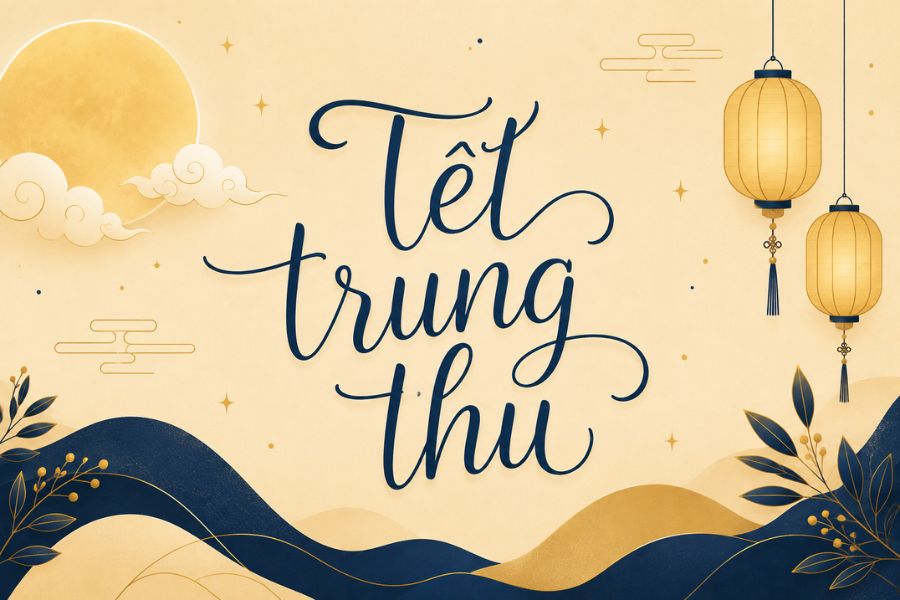
Font chữ trung thu là gì?
Font chữ trung thu là các bộ phông mang phong cách nghệ thuật đặc trưng, mô phỏng nét bút lông thư pháp uyển chuyển hoặc các đường nét tròn trịa gợi nhắc đến hình ảnh vầng trăng rằm. Điểm nổi bật của dòng font này là sự kết hợp giữa tính truyền thống dân gian và nét hiện đại, giúp truyền tải thông điệp về sự đoàn viên, hạnh phúc và thịnh vượng. Trong ngành in ấn, việc sử dụng phông chữ này giúp các mẫu thiết kế trở nên sinh động và đậm chất văn hóa Á Đông.
Tuy nhiên, do đặc thù tiếng Việt có hệ thống dấu thanh phức tạp, nhiều bộ phông quốc tế khi áp dụng vào thiết kế thường bị lỗi nhảy chữ hoặc mất dấu. Bộ font chữ việt hóa trung thu được In Viva chia sẻ đã được tinh chỉnh kỹ lưỡng, đảm bảo từng dấu mũ, dấu thanh đều hài hòa với nét chữ gốc. Điều này giúp các designer tiết kiệm thời gian chỉnh sửa thủ công và tập trung tối đa vào việc sáng tạo bố cục cho các ấn phẩm và bao bì giấy.
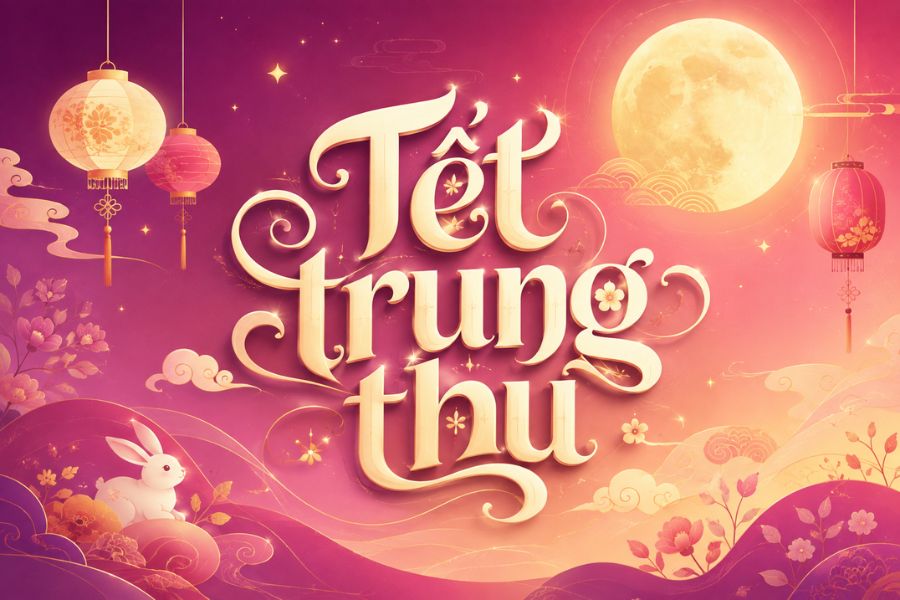
Lưu ý: Khi sử dụng font chữ trung thu đẹp cho mục đích in hộp giấy cao cấp, bạn nên ưu tiên hệ màu CMYK và phối hợp cùng các tông màu đỏ chu sa, vàng kim nhũ để tôn lên vẻ đẹp truyền thống của bộ chữ.
5 ứng dụng chính của font chữ trung thu trong thiết kế và in ấn
Việc sử dụng đúng font chữ giúp nâng tầm giá trị cho món quà tri ân trong mùa lễ hội đoàn viên:
- Thiết kế bao bì hộp bánh trung thu: Font chữ trung thu việt hóa được dùng cho tên thương hiệu hoặc các câu chúc như “Vạn Sự Như Ý“, “Nguyệt Viên Trung Thu“. In Viva thường kết hợp font này với kỹ thuật ép kim nhũ vàng trên nền hộp cứng để tạo hiệu ứng sang trọng.
- Sản xuất túi giấy quà tặng sự kiện: Túi giấy đi kèm hộp bánh cần sự đồng bộ về phông chữ và màu sắc. Sử dụng font trung thu sắc nét giúp túi giấy trở thành công cụ marketing hiệu quả, ghi dấu ấn thương hiệu mạnh mẽ trong lòng khách hàng.
- Thiết kế backdrop và banner sự kiện: Trong các đêm hội trăng rằm cho thiếu nhi hoặc sự kiện nội bộ công ty, font chữ trung thu đẹp khổ lớn giúp phông nền sân khấu trở nên hoành tráng, thu hút sự chú ý của mọi người từ xa.
- In ấn voucher và thẻ quà tặng mùa lễ: Font chữ mềm mại, đậm chất nghệ thuật giúp các tấm thẻ giảm giá hay thiệp tri ân trở nên tinh tế hơn, khiến người nhận cảm thấy được trân trọng và quan tâm.
- Quà tặng gốm sứ in logo: Chữ thư pháp trung thu được in nung trên bộ ấm chén gốm sứ Bát Tràng tạo nên bộ quà tặng đối ngoại vô cùng ý nghĩa. Công nghệ in nung tại In Viva giúp nét chữ bám màu bền đẹp theo thời gian.
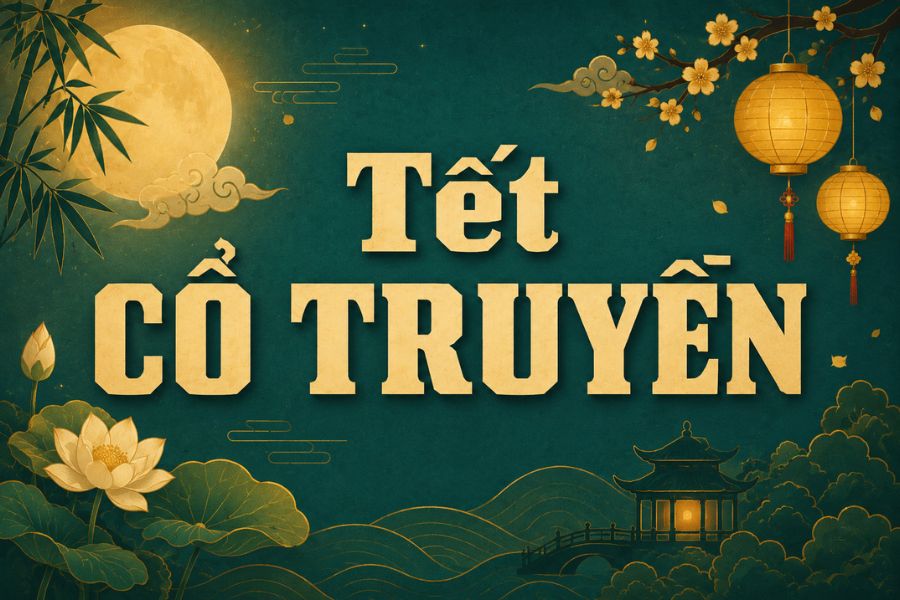
4 lưu ý khi sử dụng font trung thu việt hóa free
Để bản thiết kế chuyển thể thành thành phẩm in ấn hoàn hảo nhất, designer cần nắm vững các kỹ thuật sau:
- Kiểm soát độ đậm nhạt của nét bút: Font trung thu có các nét xước hoặc nét thanh rất mảnh. Khi in lụa trên túi vải hoặc túi giấy nhám, bạn nên tăng nhẹ độ dày Stroke để mực in thoát đều, tránh tình trạng chữ bị đứt đoạn.
- Tối ưu đường Path cho gia công bế nổi: Khi dập nổi logo hoặc lời chúc trên nắp hộp cứng nên xử lý mịn mọi điểm neo trong file vector để khuôn bế thực hiện chính xác, tạo độ nổi khối sắc sảo mà không làm rách mép giấy.
- Lựa chọn hệ màu CMYK chuẩn lễ hội: Màu đỏ và vàng trong thiết kế trung thu rất dễ bị lệch tông khi in Offset. Bạn nên thiết lập đúng mã màu chuẩn và thảo luận với xưởng in để bản in đạt độ rực rỡ nhất dưới ánh đèn.
- Convert phông chữ trước khi gửi xưởng: Để tránh lỗi nhảy font tại máy in của xưởng, hãy luôn thực hiện lệnh Create Outlines (Ctrl+Shift+O) cho toàn bộ nội dung bản vẽ trước khi gửi tệp tin sản xuất.